ゴシック体
ゴシック体(ごしっくたい)は印刷で用いられる書体の一つ。縦線と横線が同じ太さになっています。欧文フォントのサンセリフ体に似ています。
※=半角文字だけプロポーショナルフォント。
游書体
游書体は等幅フォントとプロポーショナルフォントの両方の特性を合わせもったフォント。「 Light」「Demibold」は太さの違いを表す。
游ゴシック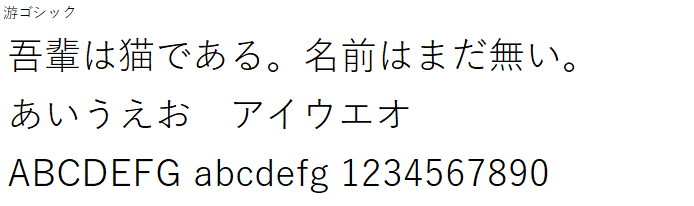
游ゴシック Light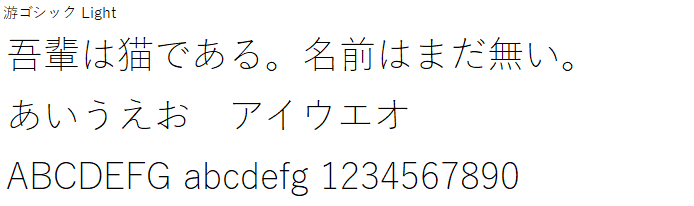
游ゴシック Medium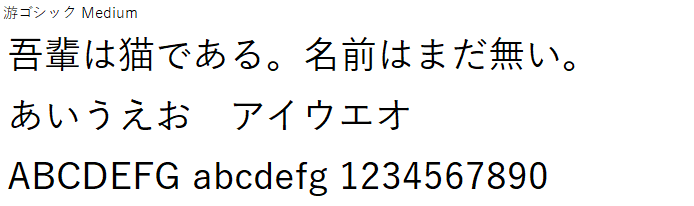
MS書体
游書体が登場するまではオフィスソフトの標準フォントだった。
MS ゴシック(等幅フォント)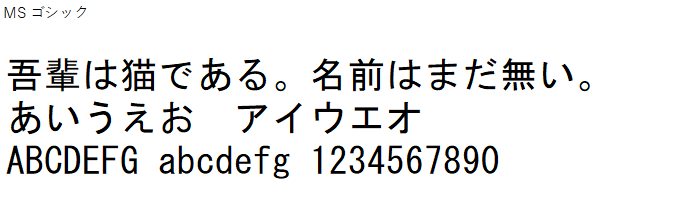
MS Pゴシック(プロポーショナルフォント)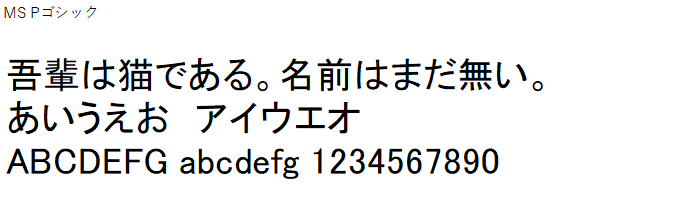
ユニバーサルデザイン書体
ユニバーサルデザイン書体は、可読性・視認性・判読性が高くなるようにデザインされたフォント。UDと略す。
BIZ UDゴシック(等幅フォント)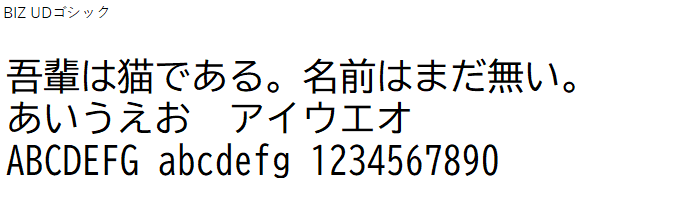
BIZ UDPゴシック(プロポーショナルフォント)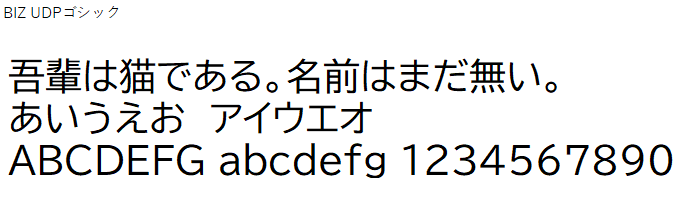
メイリオ
メイリオには文字表示をなめらかに見せる「ClearType」という技術が使われており、文字の輪郭がなめらかにできています。よって、モニターで見たときの視認性に優れています。また、ゴシック体のみです。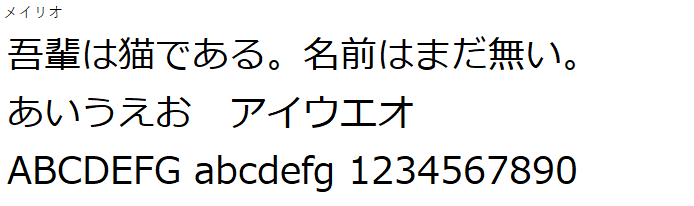
HG書体
HGは「High Grade」の略で、M・E・UBは文字の太さを表す。
HGゴシックM(等幅フォント)
HGPゴシックM(プロポーショナルフォント)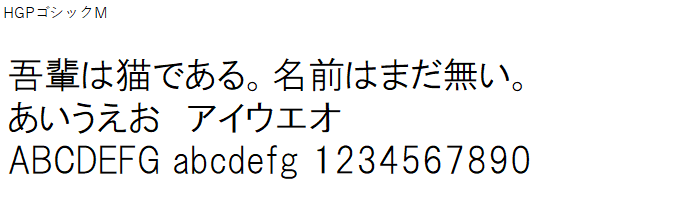
HGSゴシックM※半角文字だけプロポーショナルフォント。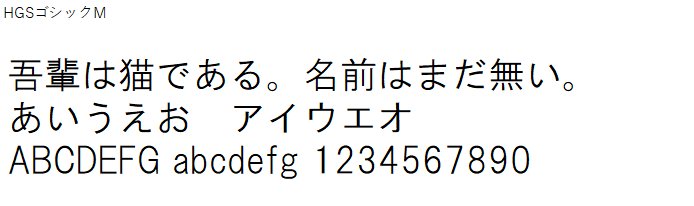
HGゴシックE(等幅フォント)
HGPゴシックE(プロポーショナルフォント)
HGSゴシックE※半角文字だけプロポーショナルフォント。
HG創英角ゴシックUB(等幅フォント)
HGP創英角ゴシックUB(プロポーショナルフォント)
HGS創英角ゴシックUB※半角文字だけプロポーショナルフォント。
HG丸ゴシックM-PRO(等幅フォント)